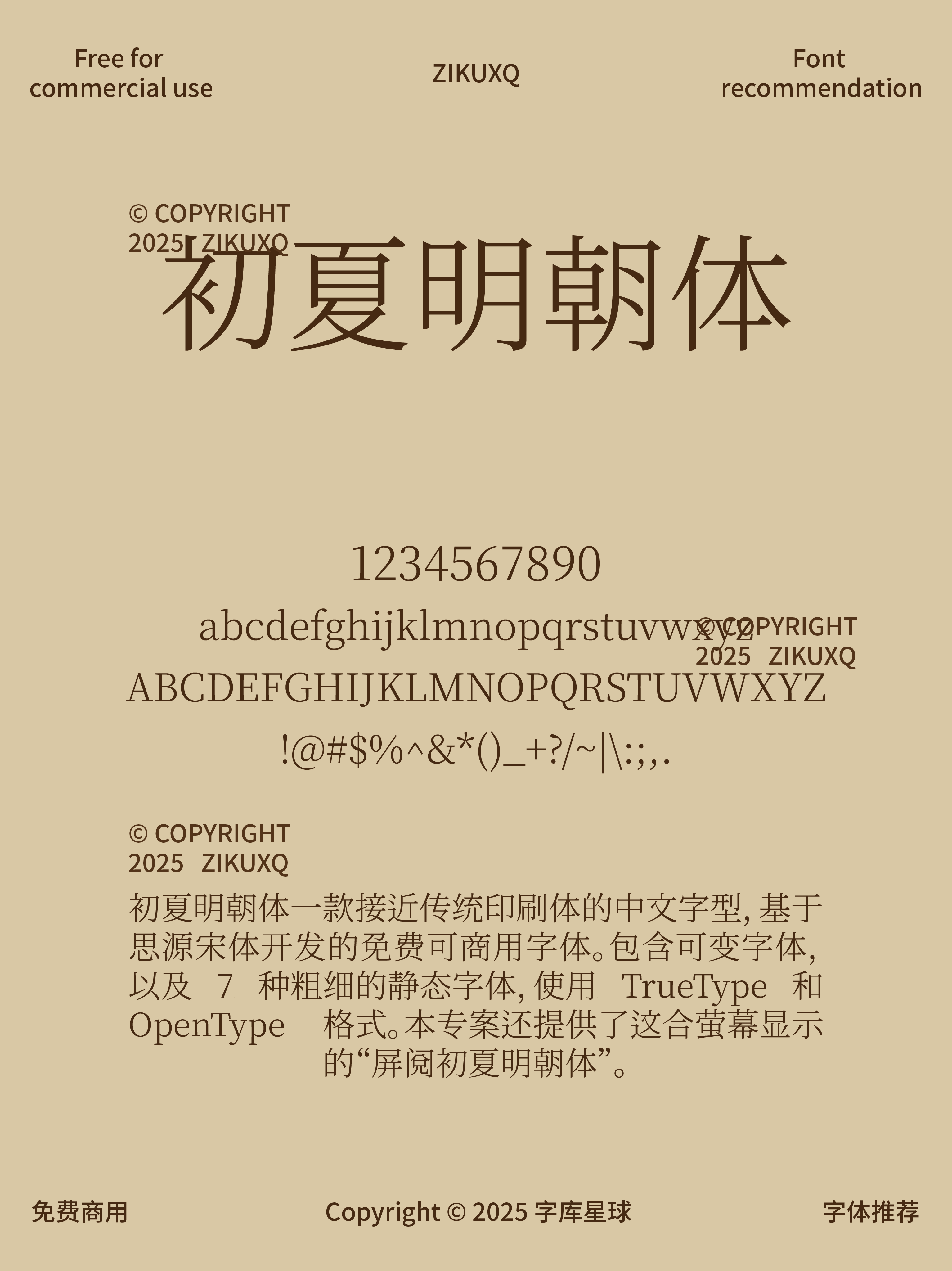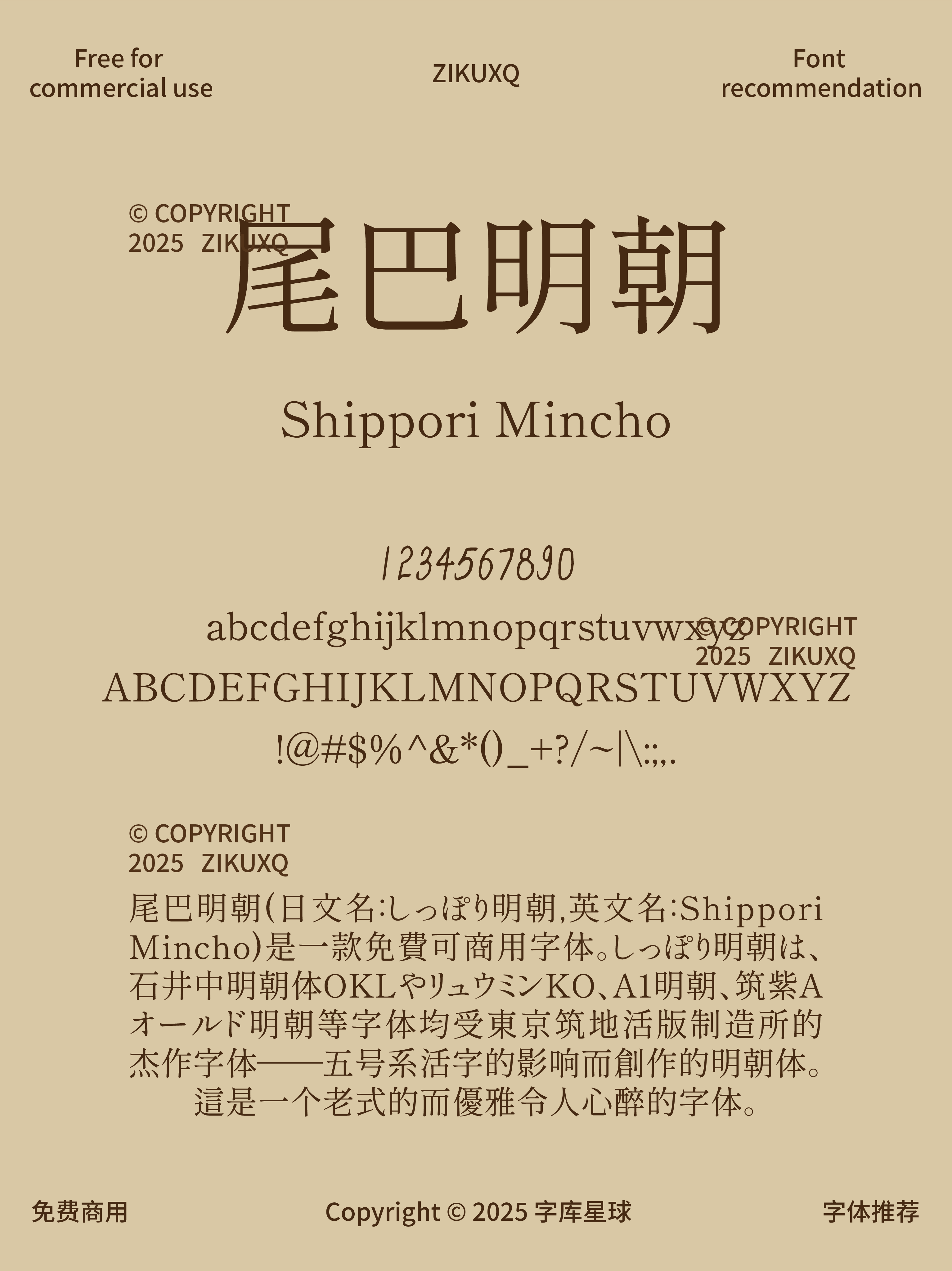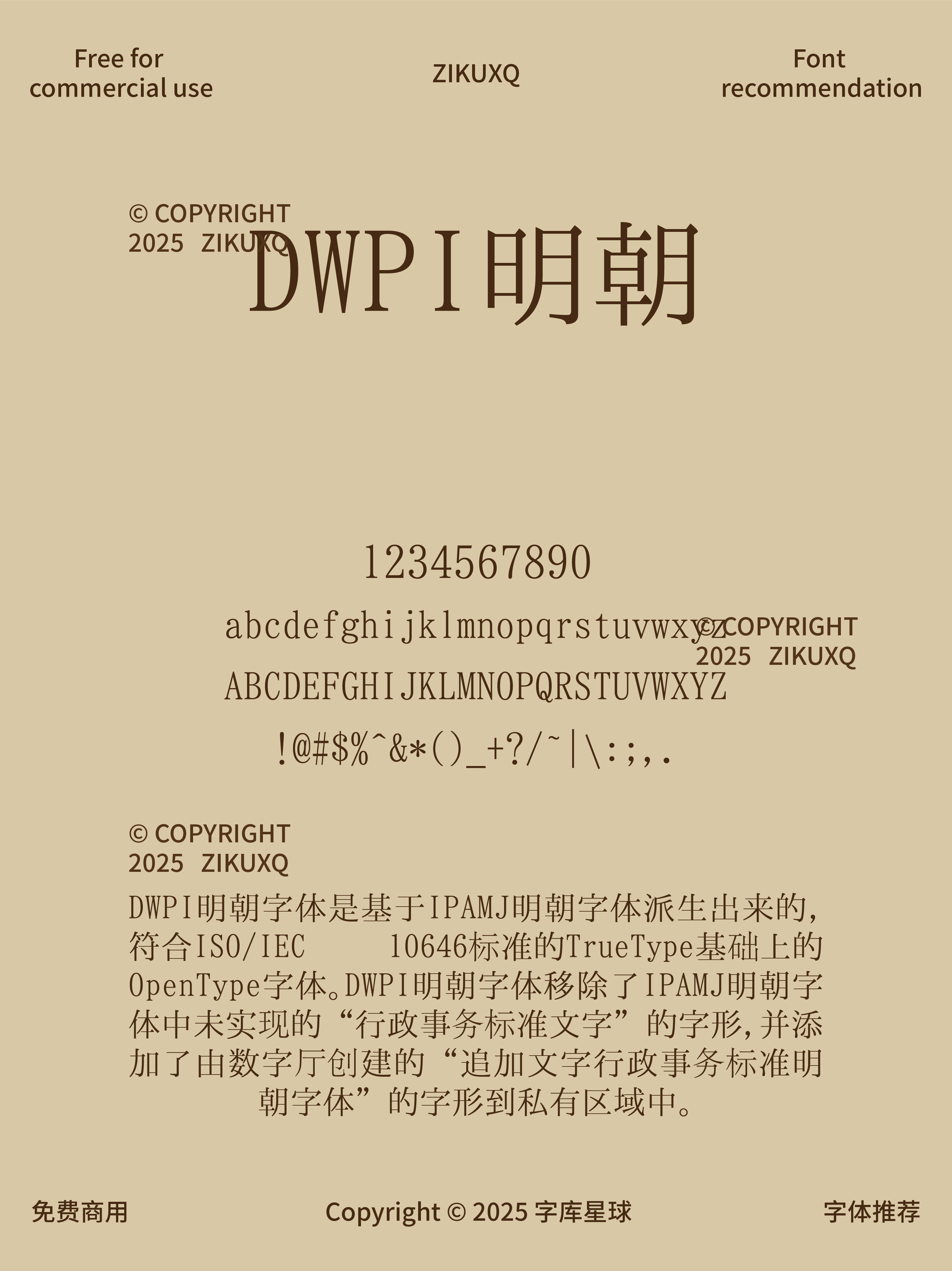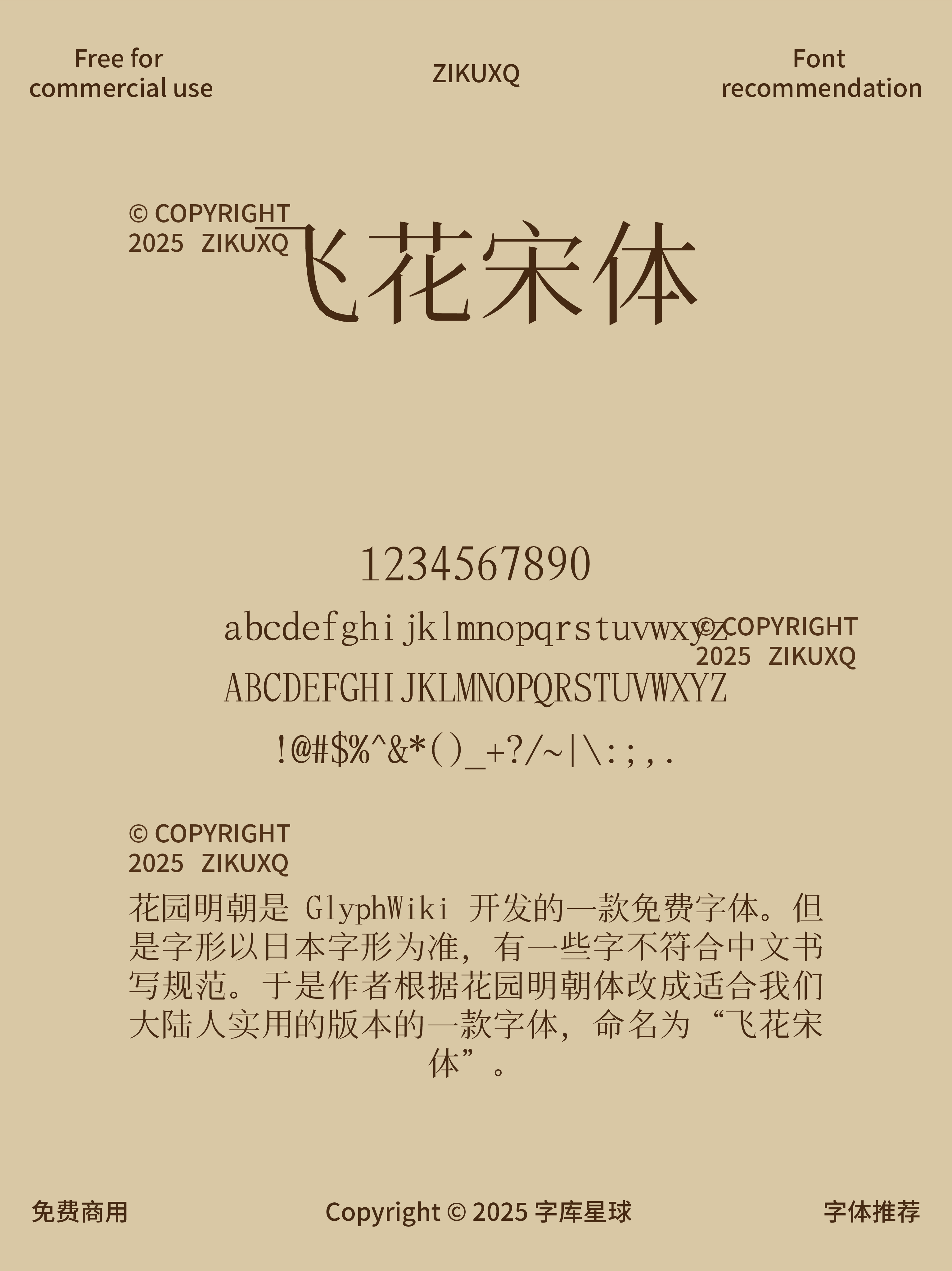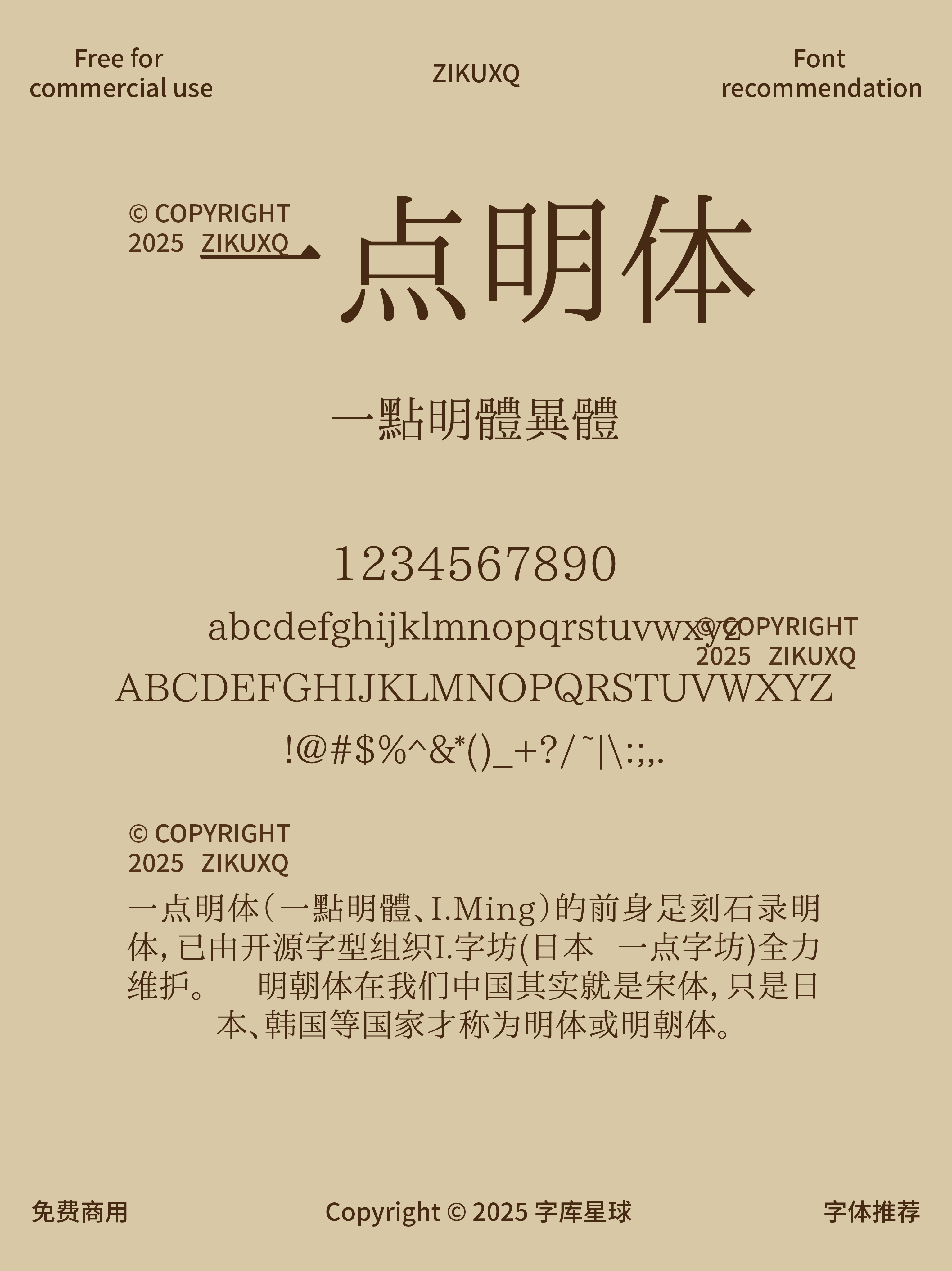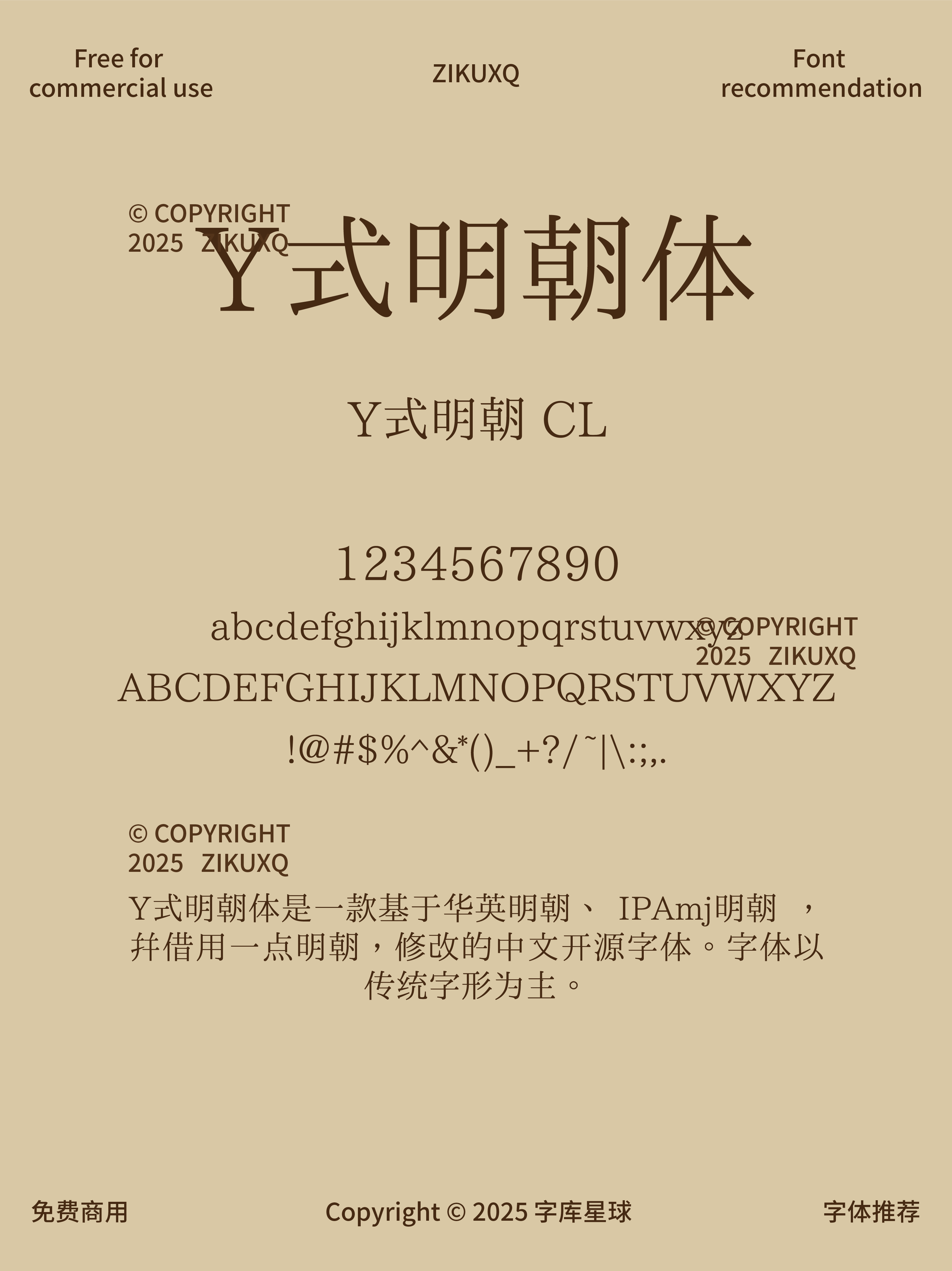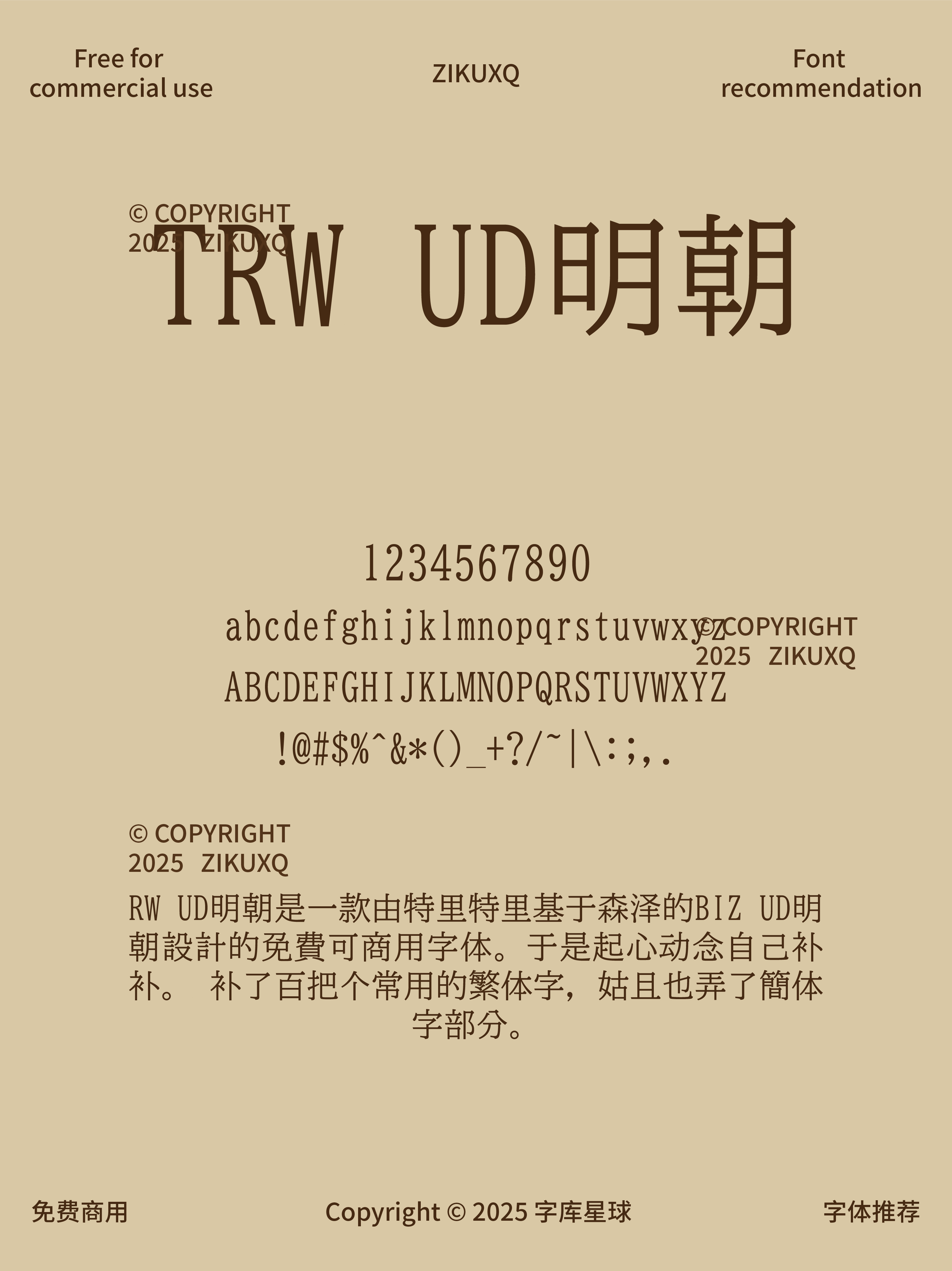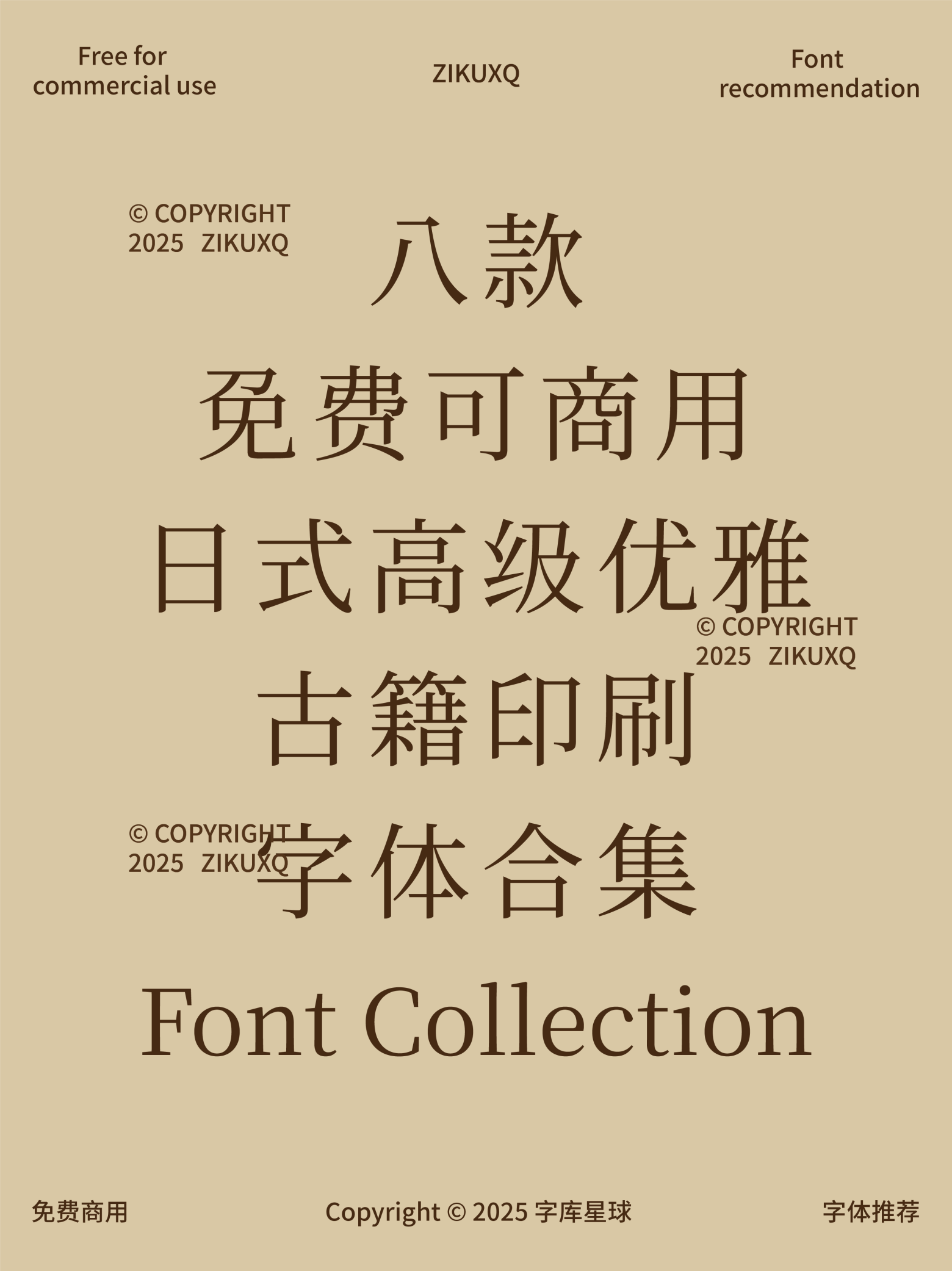
八款免费可商用日式高级优雅古籍印刷字体
八款自带高级滤镜的日式古籍印刷宋体,每一款都把优雅刻进 DNA 里,古籍排版、文艺设计直接封神!关键还不用怕侵权,快收好这份宝藏清单。
每一款字体都藏着东方美学的浪漫,笔触间流转着岁月沉淀的韵味。横竖撇捺的弧度像是水墨画里的笔触,笔画纤细如丝,透着古典书卷气,文艺风排版绝配,字形硬朗又不失柔美,复古海报秒变高级艺术品。